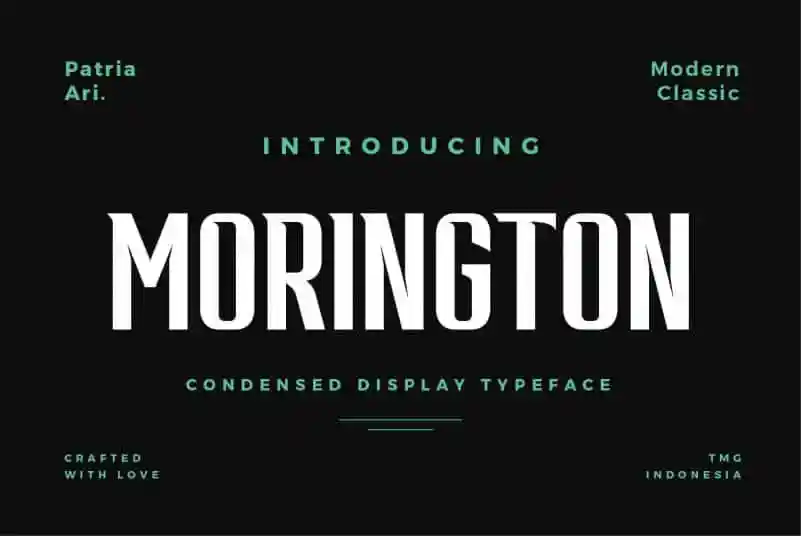
Morington Font
Morington é uma fonte display condensada que oferece caracteres robustos para fortalecer seu projeto ou marca. Ideal tanto para temáticas modernas quanto clássicas, esta fonte atende a um vasto espectro de necessidades designísticas. Ela se destaca especialmente em projetos como logomarcas e identidade visual, headlines, outdoors, rótulos, embalagens, fotografias e até mesmo eventos especiais. Com Morington, você encontra uma ferramenta poderosa para expressar a essência de seu projeto em um estilo impecável que se destaca em qualquer ambiente. Seja para dar vida à sua marca ou transformar ideias em visuais memoráveis, Morington está aqui para apoiá-lo na criação de qualquer tipo de conteúdo visual.